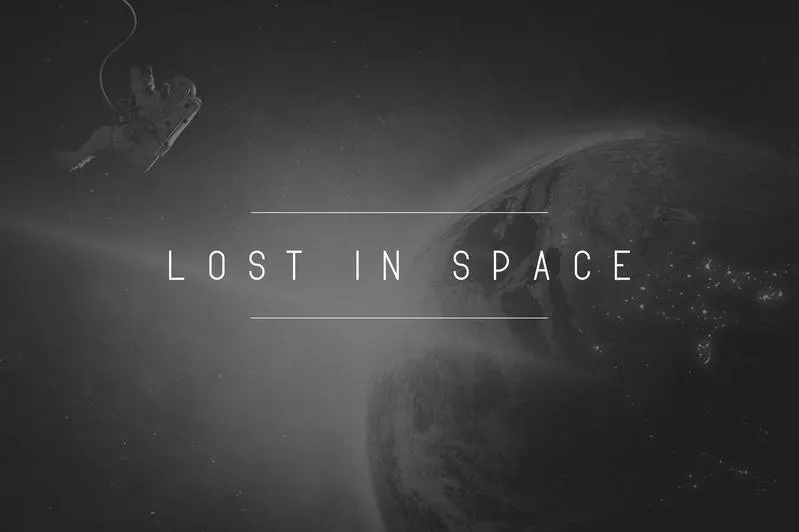
A fonte “Opinio – Sans Font Family” é uma elegante e sofisticada tipografia de tipo aberto com seis fontes disponíveis e suporte a múltiplas línguas. É uma fonte extremamente versátil que se destaca tanto em grandes como em menores tamanhos, ideal para qualquer aplicação visual onde um equilíbrio elegante seja essencial. Seja você designer de logotipos, editora ou criador de sites, a “Opinio – Sans Font Family” oferece o acabamento perfeito ao seu projeto, proporcionando uma combinação de modernidade e sofisticação que certamente irá chamar atenção. Com sua grande gama de opções, esta fonte está sempre presente na hora certa para tornar qualquer projeto um verdadeiro marco visual.